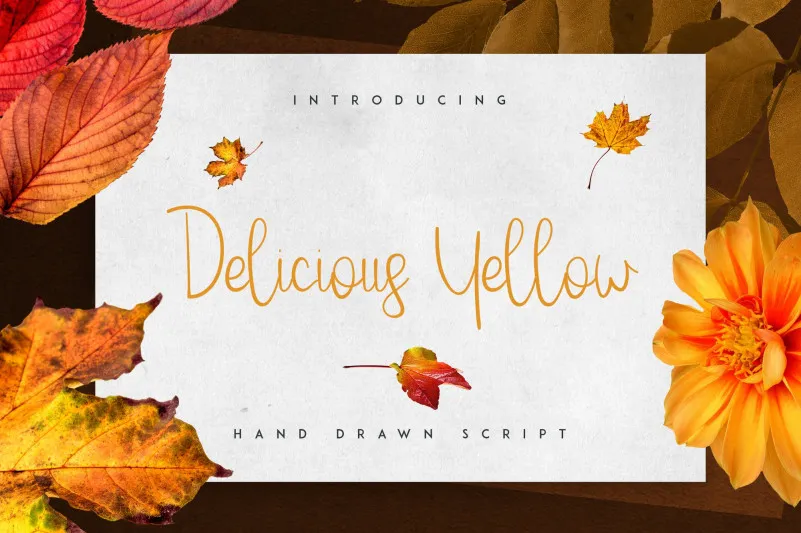
Delicious yellow Script Font – Download Grátis
Delicious Yellow Script Font é uma fonte escrita à mão com um toque pessoal e elegante. Ela oferece linhas limpas e ressaltadas que refletem a essência de quem a criou, permitindo uma adição única às marcas de identidade visual, designs de mobiliário em casa e embalagens de produtos. Além disso, sua forma permite ser usada não apenas para textos estilizados sobre fundos de imagens, mas também pode se integrar perfeitamente ao seu design digital em qualquer projeto que deseje dar um toque especial e atraente. A fonte é perfeita tanto para marcas criativas quanto para quem busca uma maneira única de destacar seu trabalho ou produto. Ela é ideal para aqueles que buscam um tom leve, personalizado e divertido para seus projetos digitais.